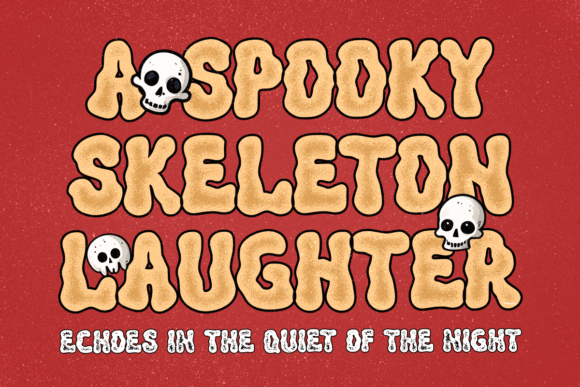
Folklore Font
Folklore Font – خط إبداعي مستوحى من الفلكلور
اكتشف سحر التراث والفن التقليدي مع Folklore Font، خط فريد مستوحى من الأنماط الفلكلورية الأصيلة. يتميز هذا الخط بتصميم أنيق يجمع بين الطابع الكلاسيكي واللمسات العصرية، مما يجعله مثالياً للمشاريع الإبداعية مثل:
Folklore Font هو الخيار الأمثل للمصممين والفنانين الذين يبحثون عن لمسة تقليدية بلمسات حداثية، مما يضفي طابعاً مميزاً على أي مشروع بصري. احصل عليه الآن وأضف لمسة من السحر الفلكلوري إلى تصاميمك! ✨